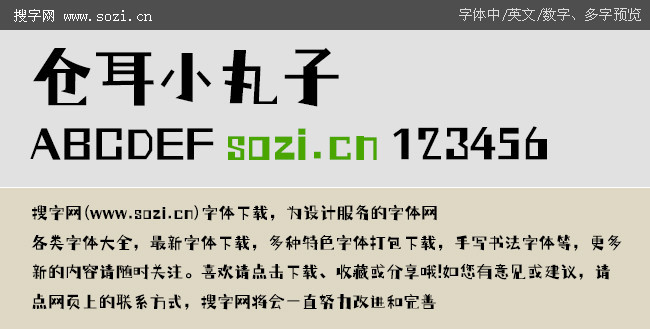
倉(cāng)耳小丸子字體
搜字網(wǎng)提供一款倉(cāng)耳小丸子字體中文藝術(shù)字體下載,倉(cāng)耳小丸子是倉(cāng)耳字庫(kù)推出的一款免費(fèi)商用字體,該字體結(jié)構(gòu)靈活,選用粗細(xì)對(duì)比夸張的筆畫,使字體更具視覺(jué)沖擊力,搞怪的字型結(jié)構(gòu)和出乎意料的空間調(diào)整讓字體多了幾分調(diào)皮可愛之氣,筆畫錯(cuò)落有致,打破了許多固有的排列模式,這款字在寬松的氛圍中營(yíng)造出天真爛漫的感受。